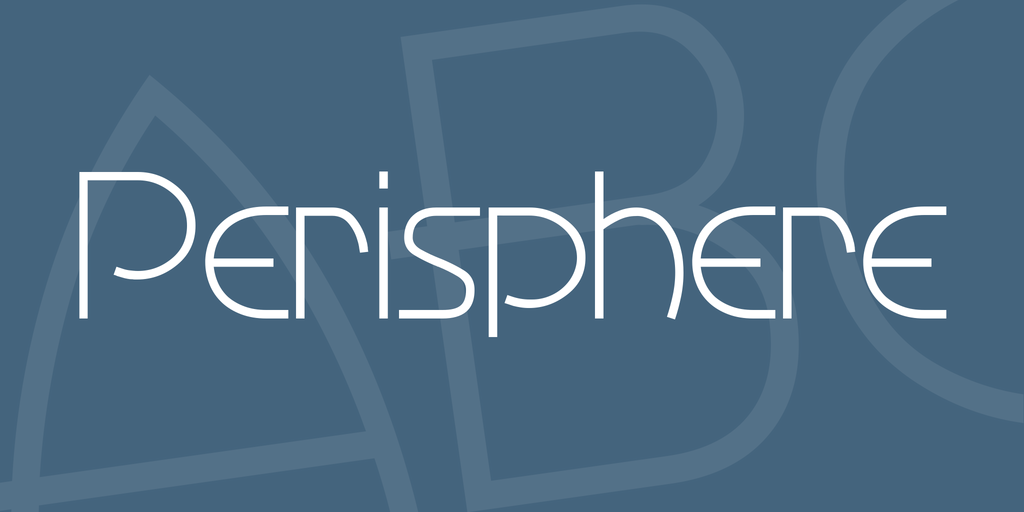
A Perisphere Font é uma revisão moderna do clássico fonte Deco chamado Advertisers Gothic. Inspirada no famoso símbolo do Trylon, que era um dos dois símbolos icônicos da 1939 New York World’s Fair, a Perisphere se distingue por sua elegância e graciosidade, com um feixe x-larguinho que se destaca entre as linhas. Este é um tipo de fonte leve, perfeito para aplicação em design retro ou vintage. É uma opção ideal para aqueles buscando trazer um toque sofisticado ao seu layout sem comprometer o charme e a elegância do estilo Deco. A Perisphere é uma escolha convidativa para designers que valorizam uma combinação de simplicidade, elegância e nostalgia no design visual de seus projetos.